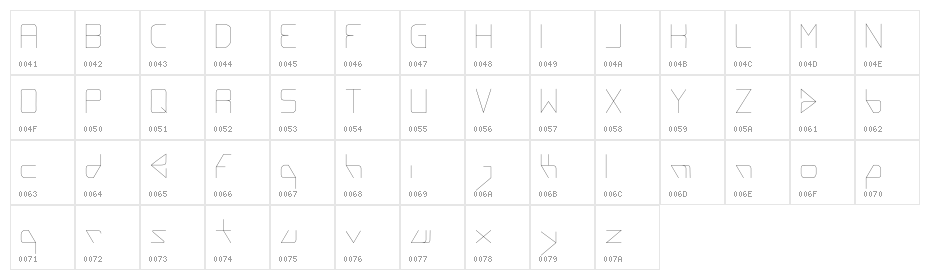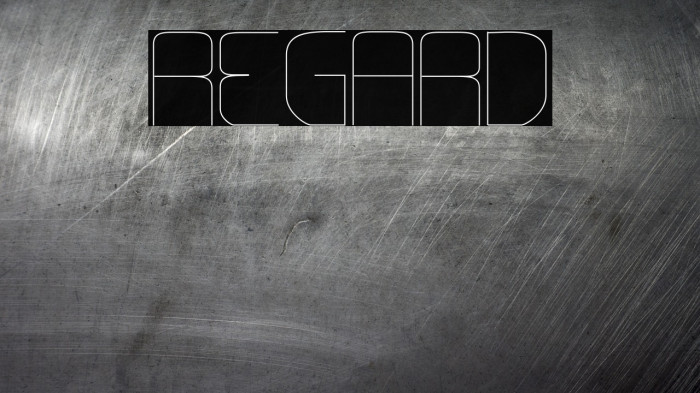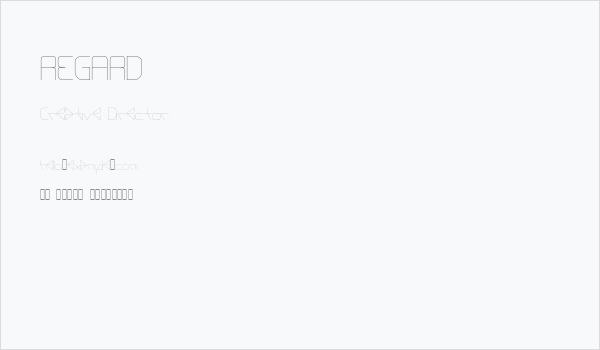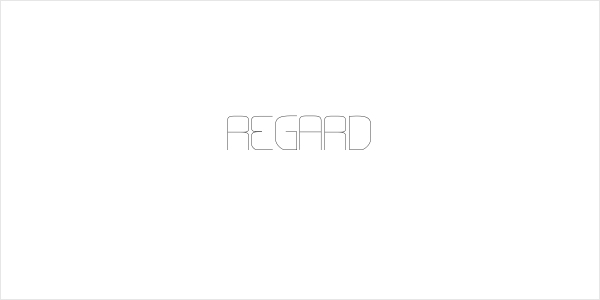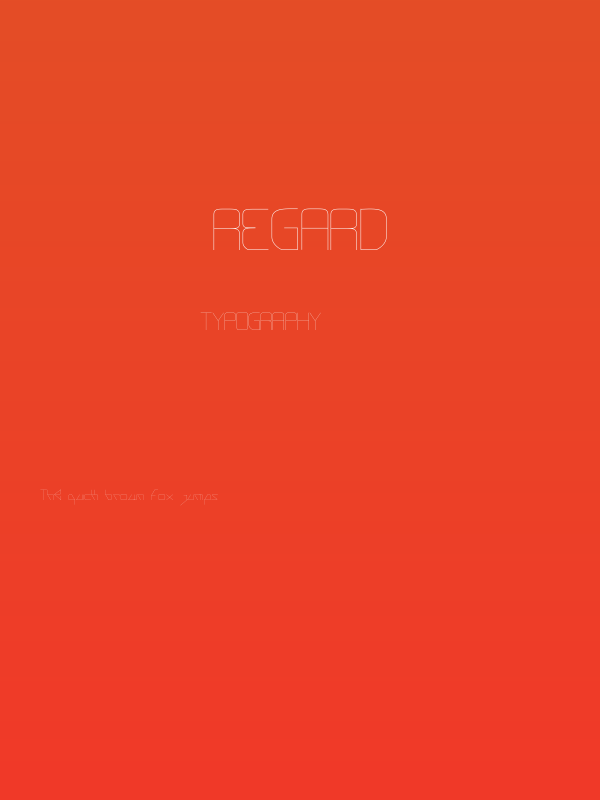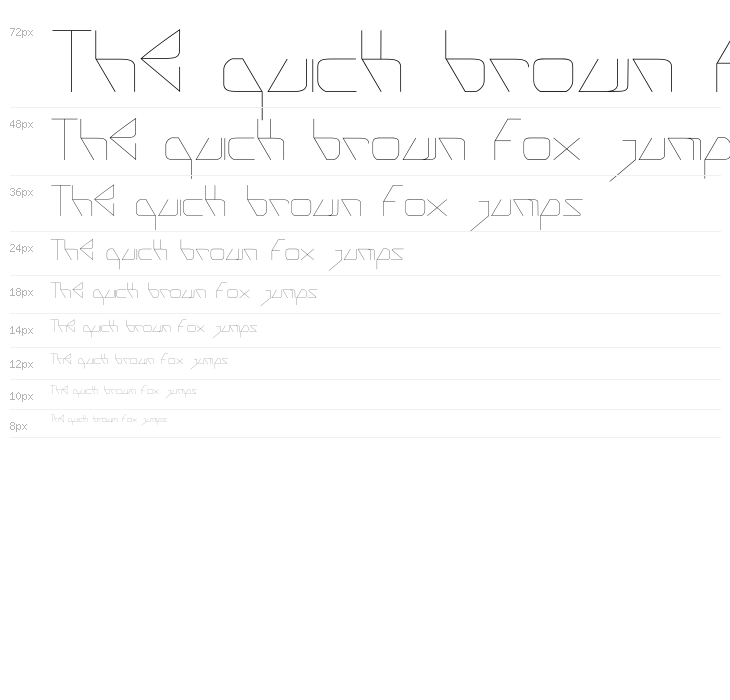
REGARD Font
| Style général | Futuristic, Technical |
| Cas d'utilisation | Logos, Headlines, Digital interfaces |
| Projets proposés | Ideal for technology branding, modern art posters, architectural designs, and digital interfaces. |